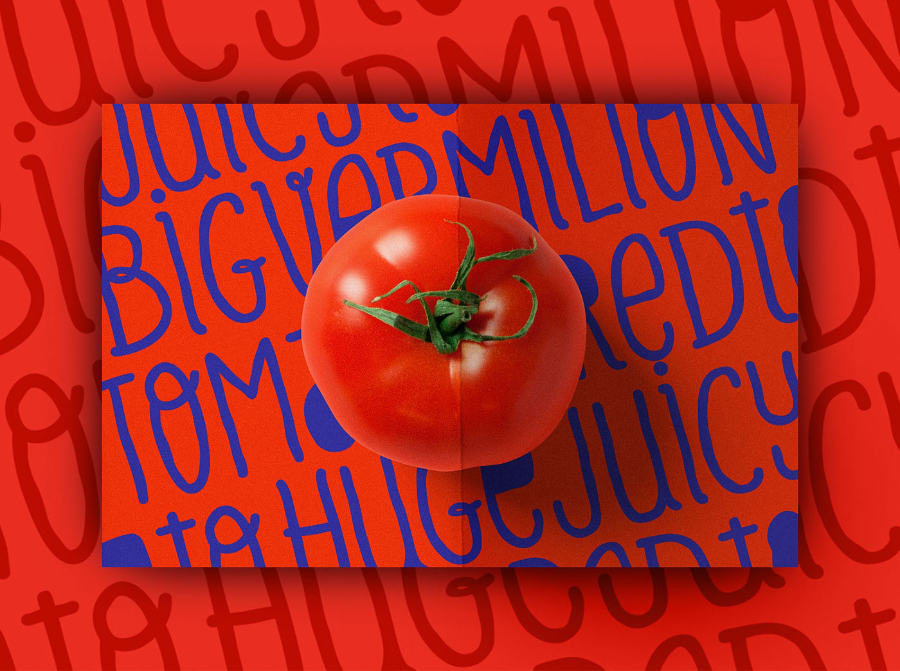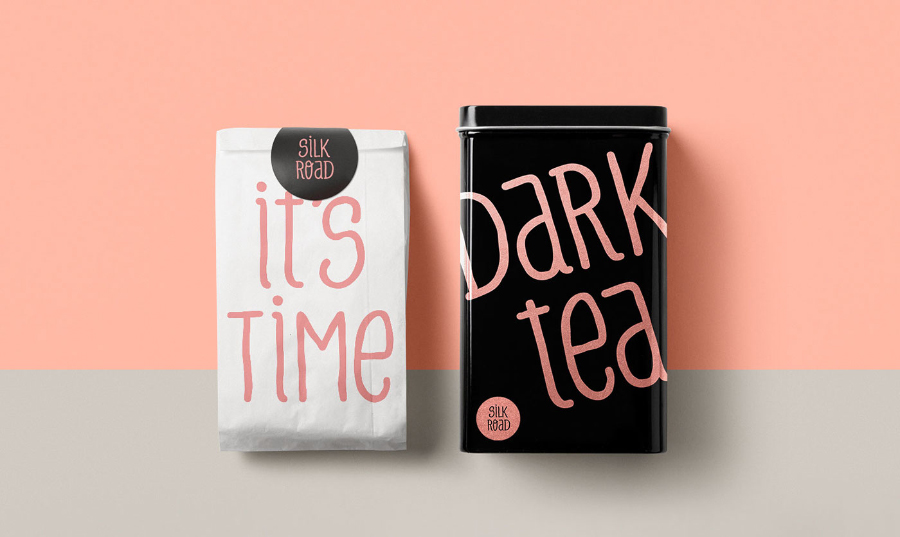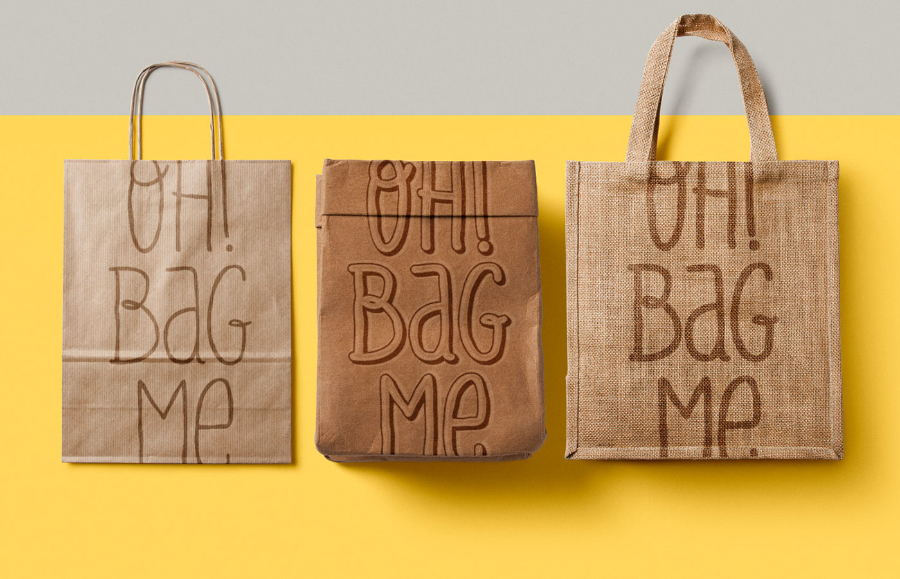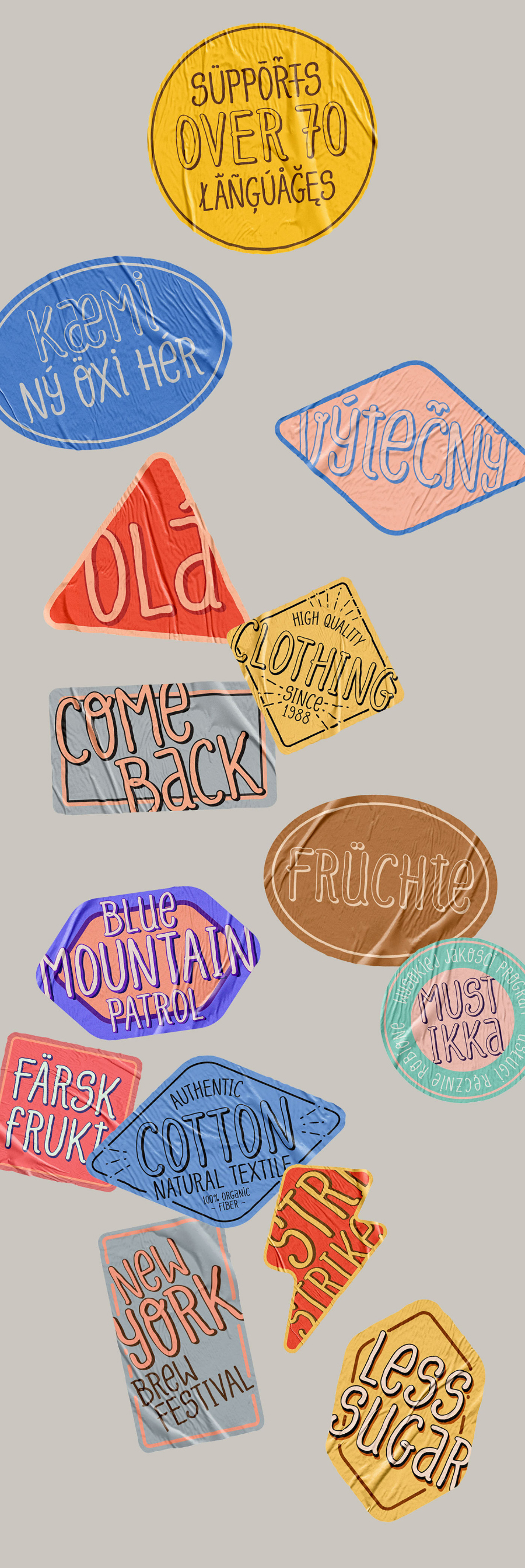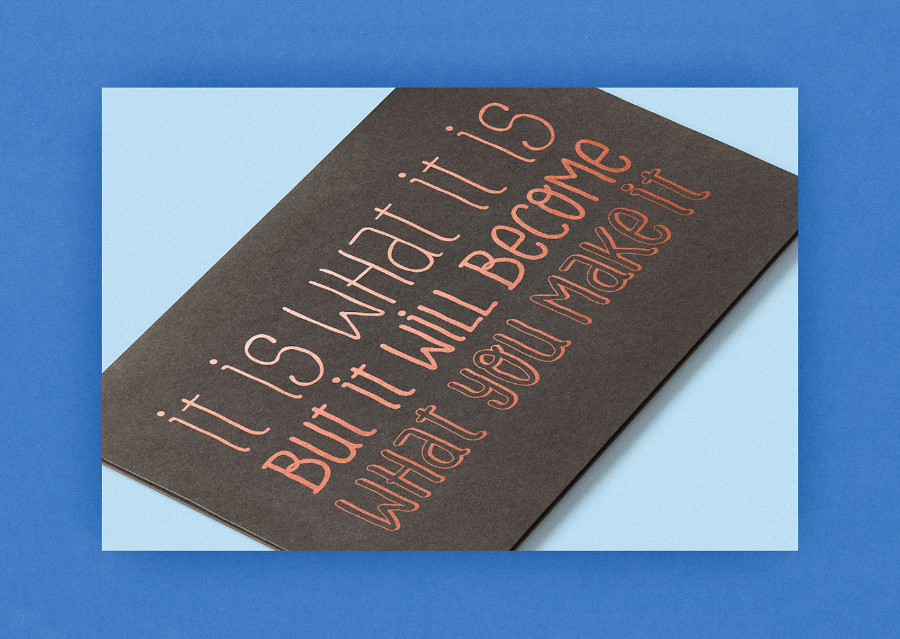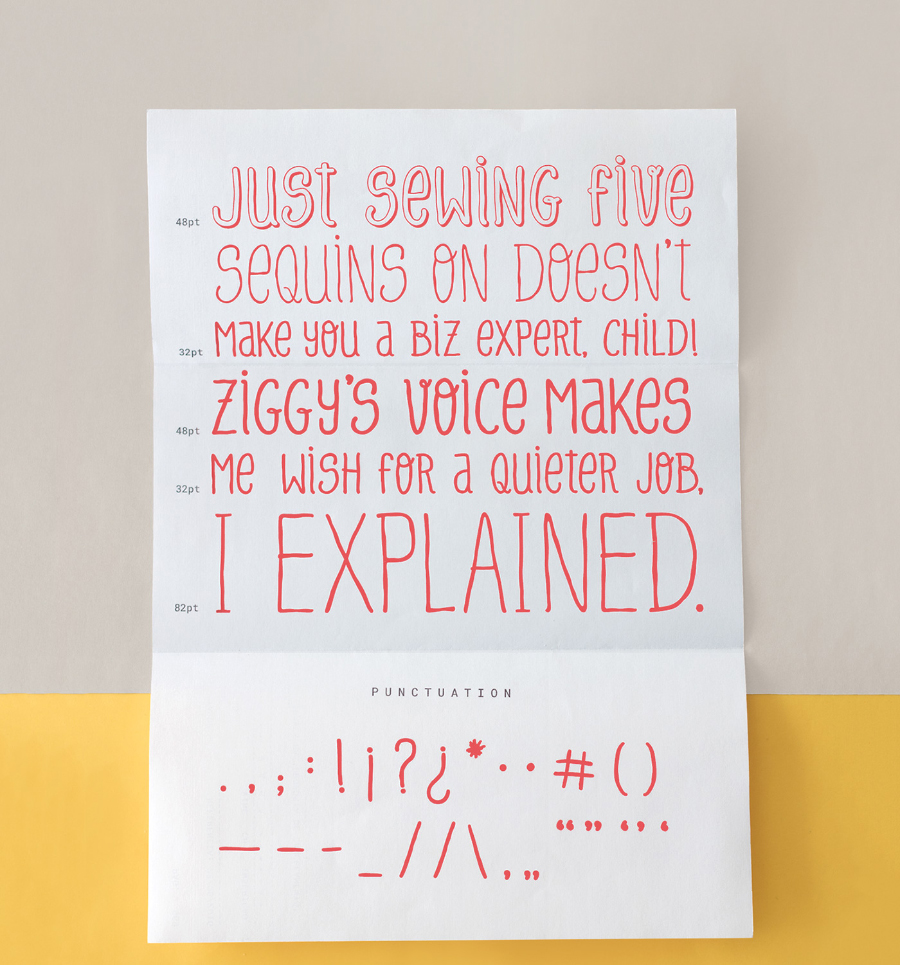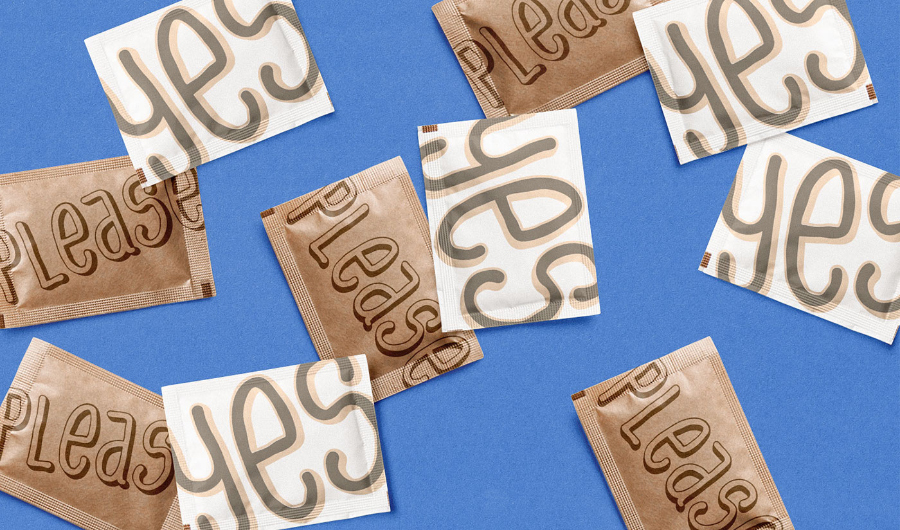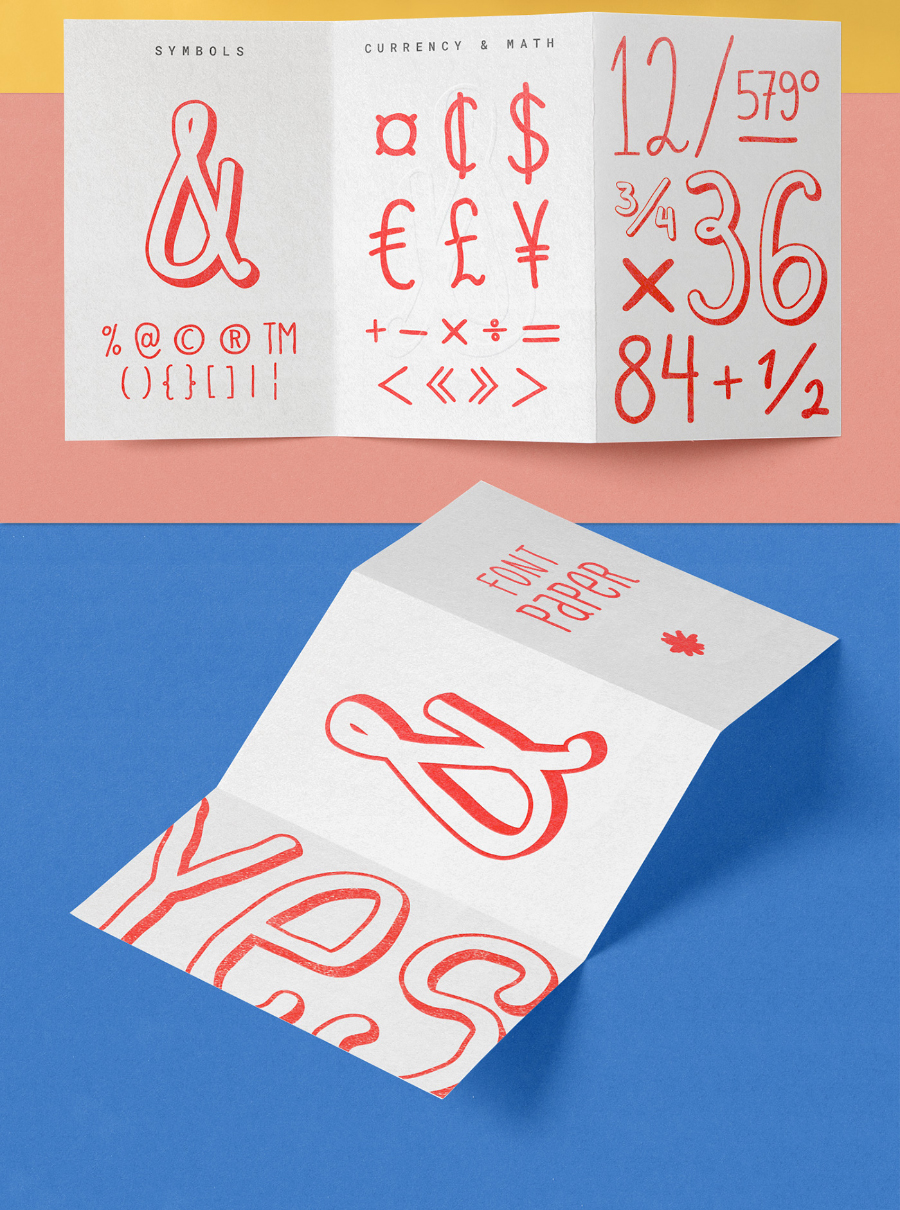
菠萝类型家庭免费演示
Pineapple Typefamily Free Demo
菠萝类家庭免费试用版是一个具有手工特征的显示字体的试用版本。这种手写字体为设计项目带来了手工美学。字体在形状上遵循独特的对比,其中厚度的穿梭变化。因此它看起来类似于一个铅笔痕迹,完美地给你的设计项目的质朴和工艺的触感!